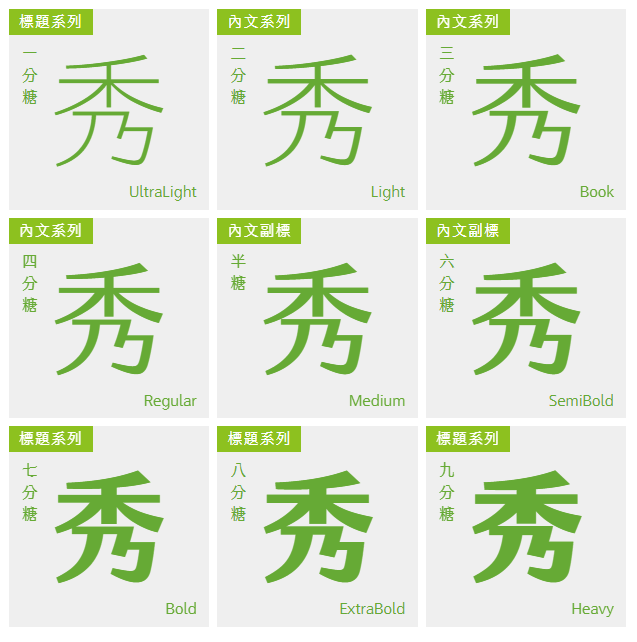
jfjinxuan3.0 世上第一個由群眾募資成真的中文字型 歷經四年,細細刻畫成為粗細齊備的家族,就等你來欣賞、品味。 對於創作而言,字型是無可或缺的工具。 對 justfont 而言,金萱字型不只是好用的工具,更是我們全心投入反覆雕琢的作品。 精密細節靠耐心磨煉,細緻韻味要時間沈澱。更重要的是精準技藝,與追求完美的決心。
合適的大小,是良好應用的關鍵!這裡歸納 justfont 團隊實驗出來的最適應用建議,供大家參考。